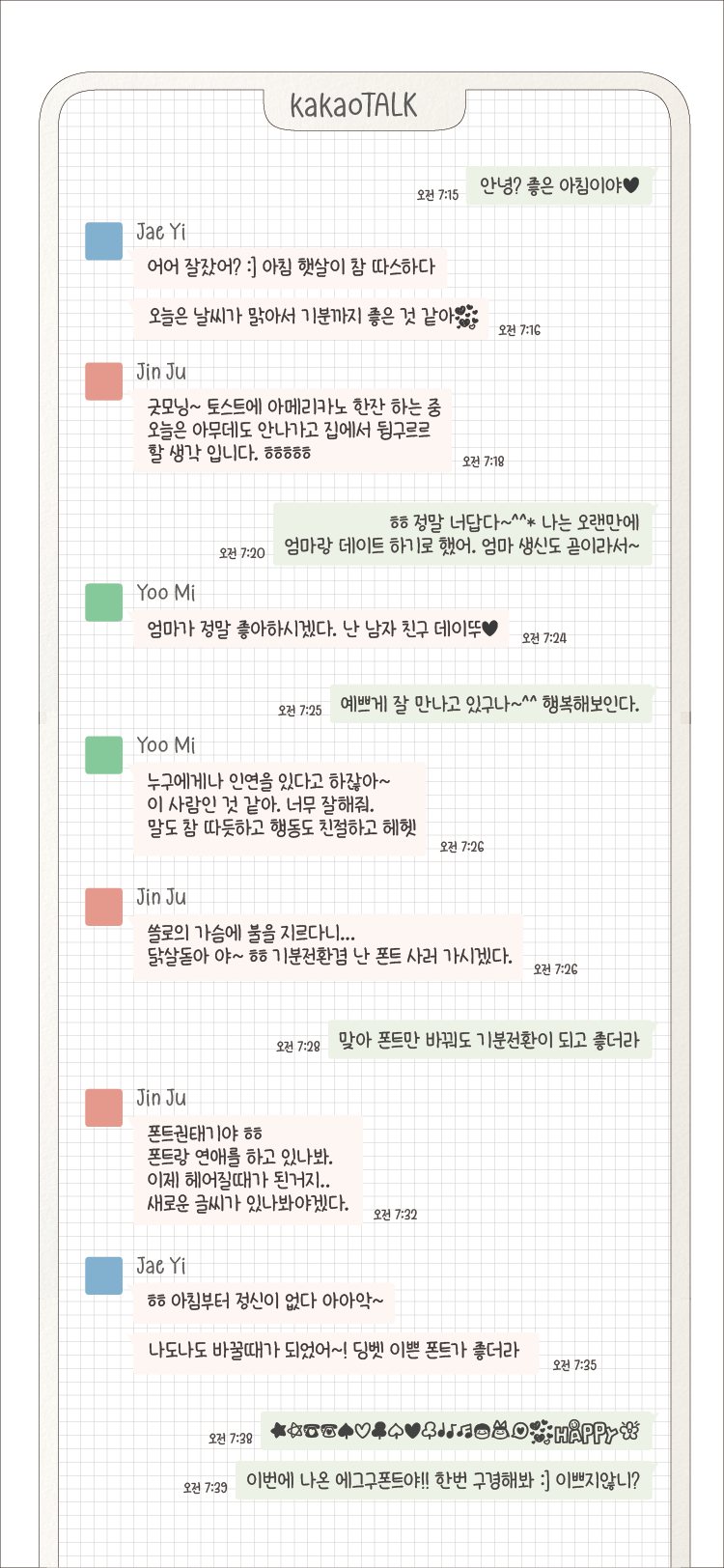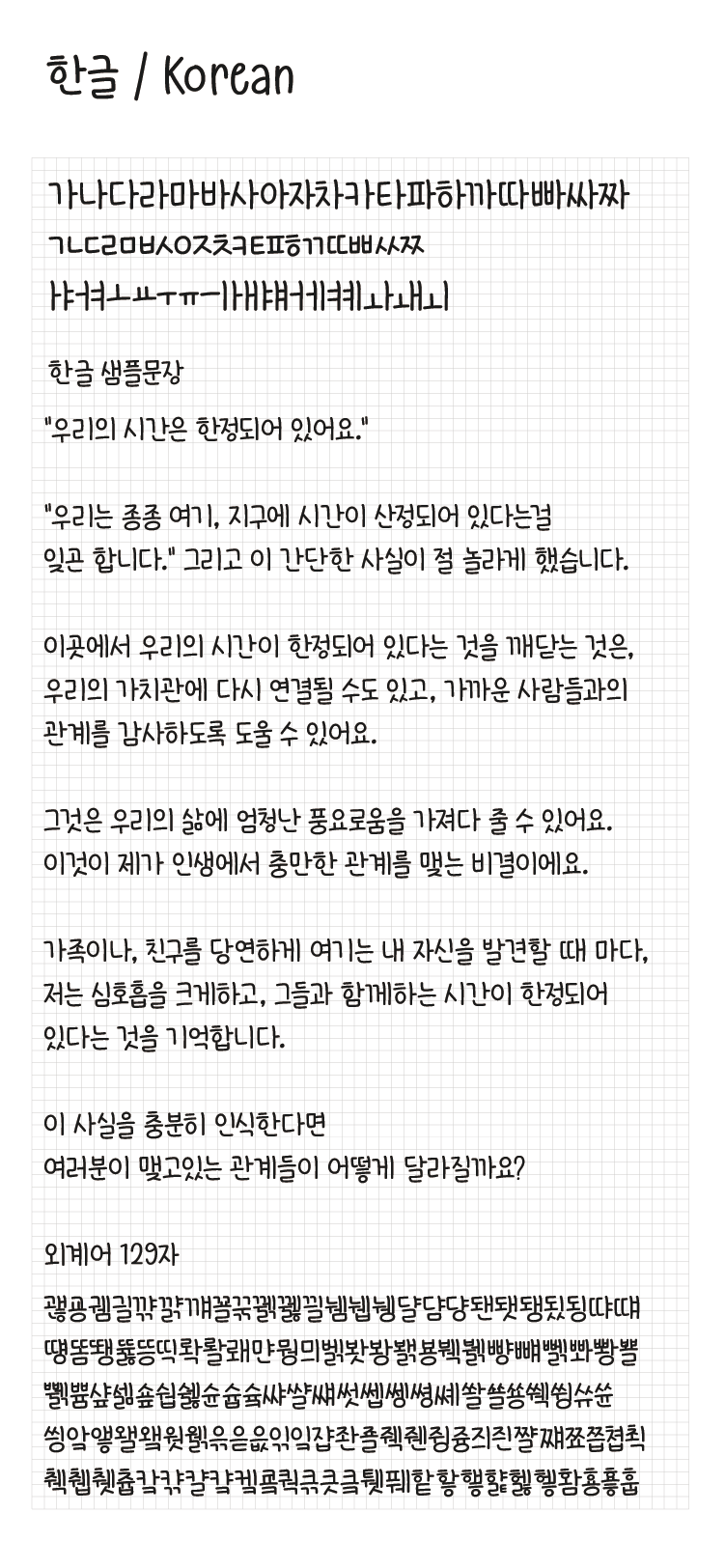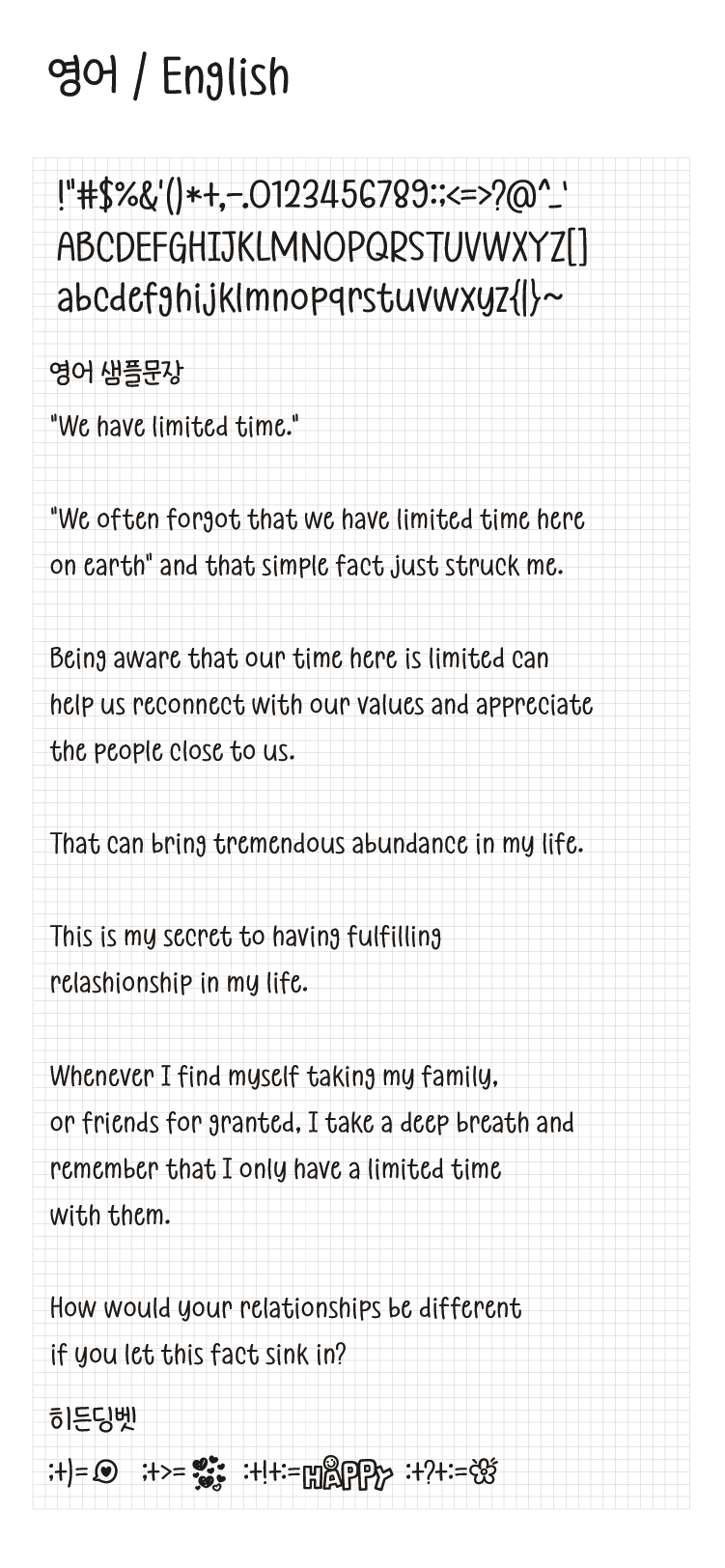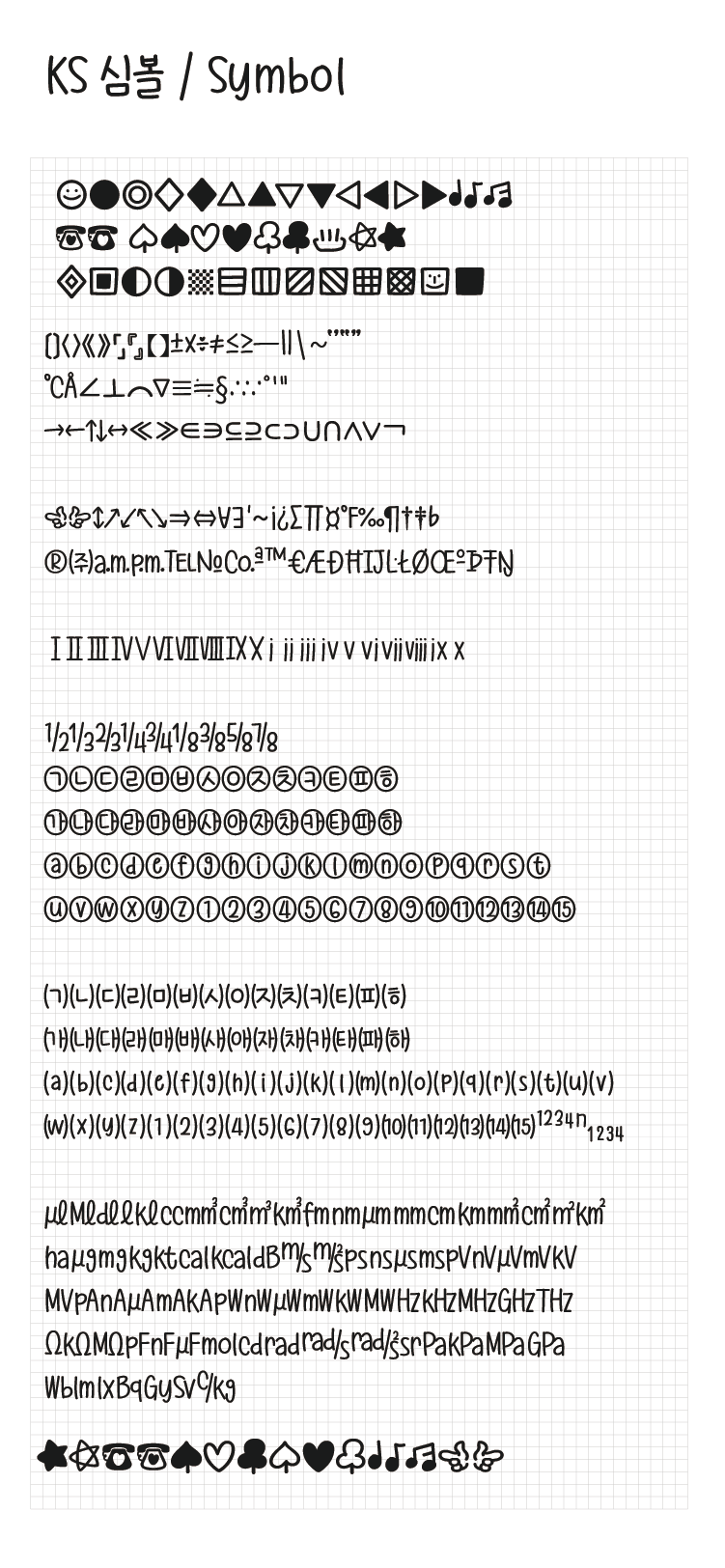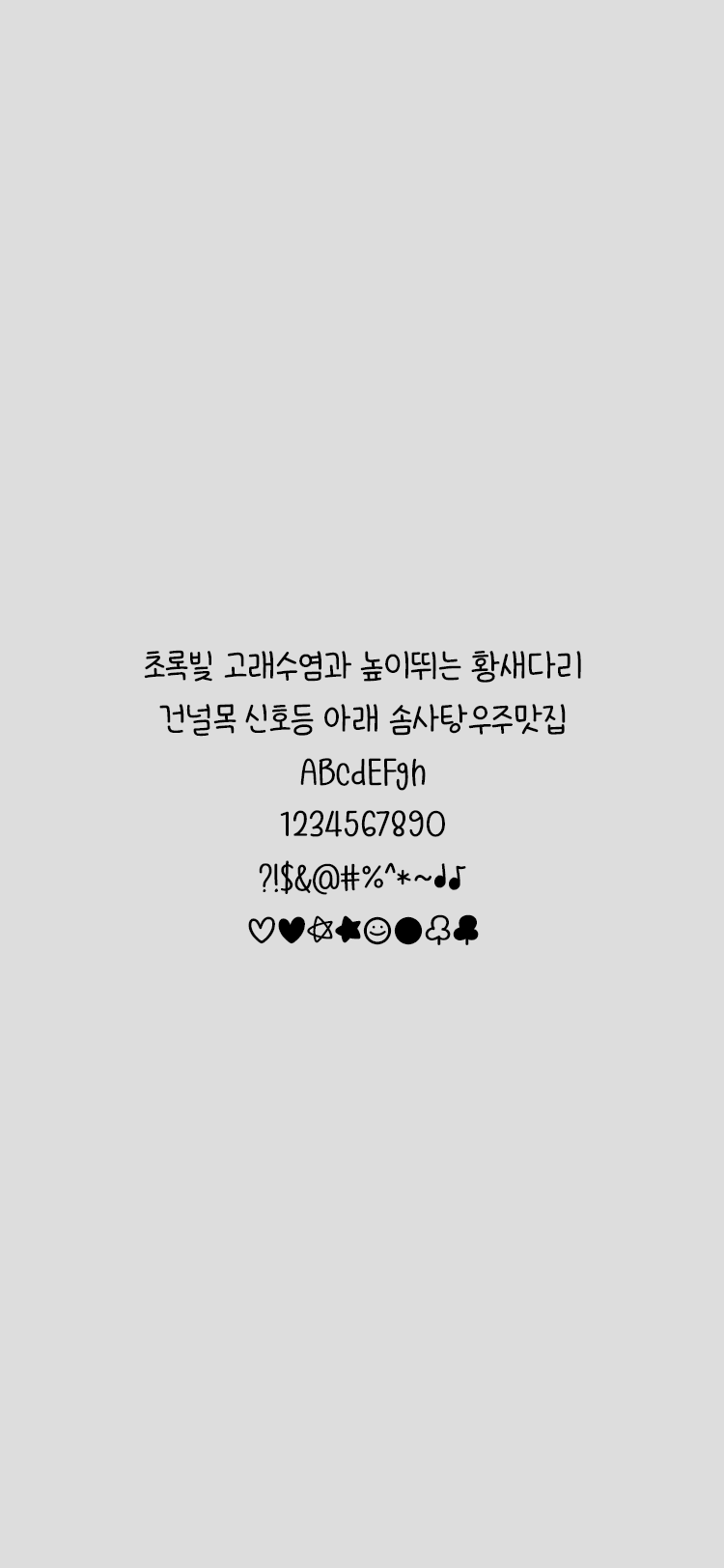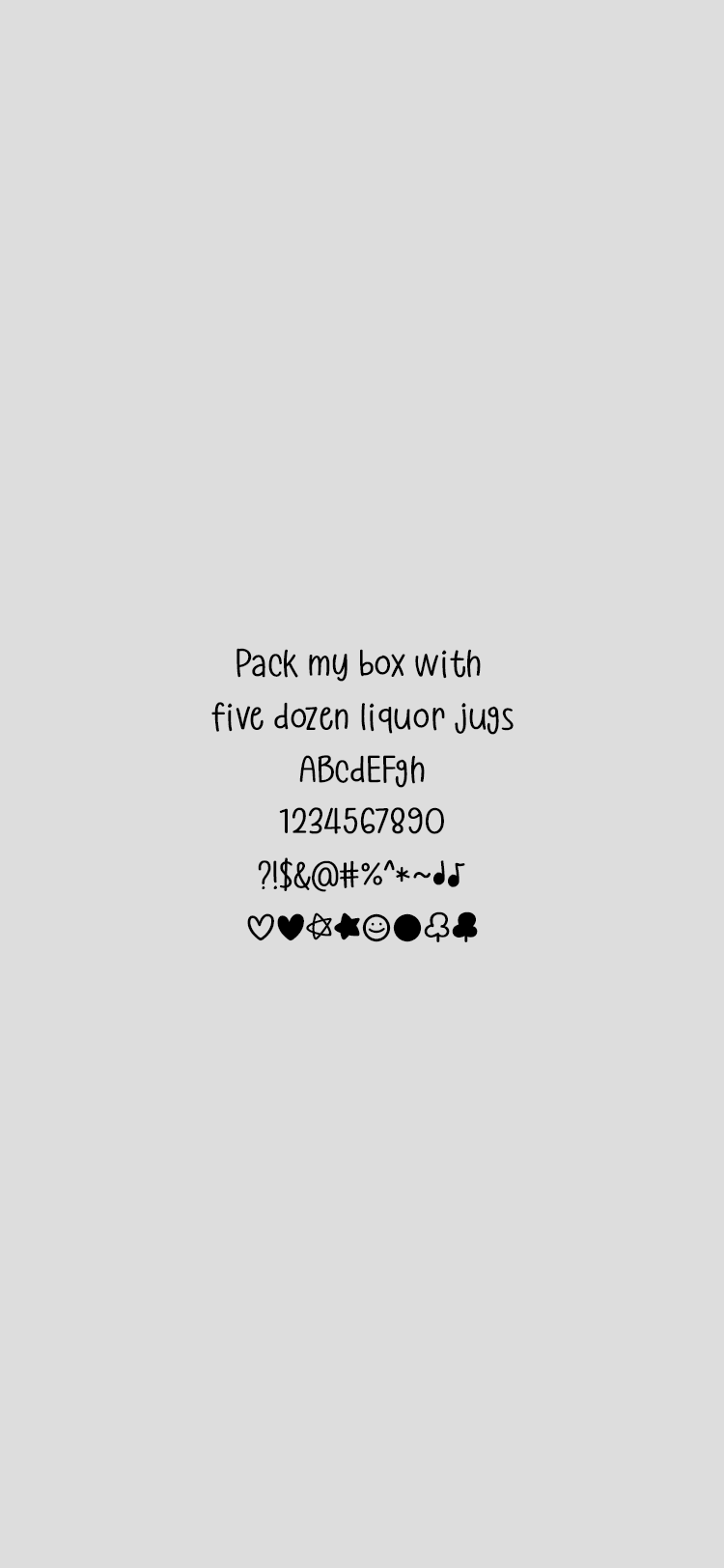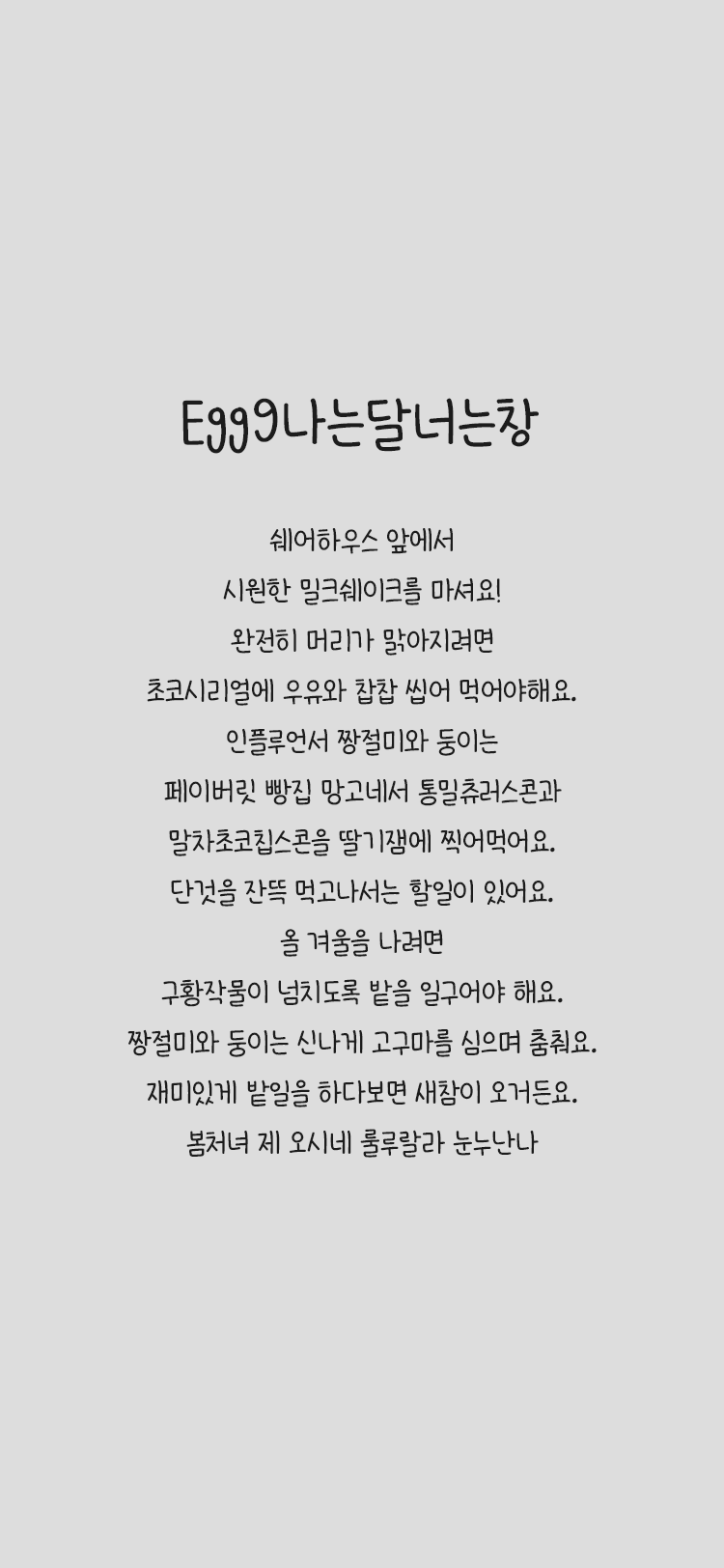
Egg9 나는달너는창
Egg9font
Egg9 나는달너는창 font in use
아기자기한 손글씨 스타일입니다. 히든딩벳의 경우 ;> ;) :!: :?: 입력하시면 나옵니다.
• 한글 11,172자 / 라틴 95자 / 부호 985자 / 추가 글리프 4자
• Egg9 나는달너는창 / Egg9 IamMoon